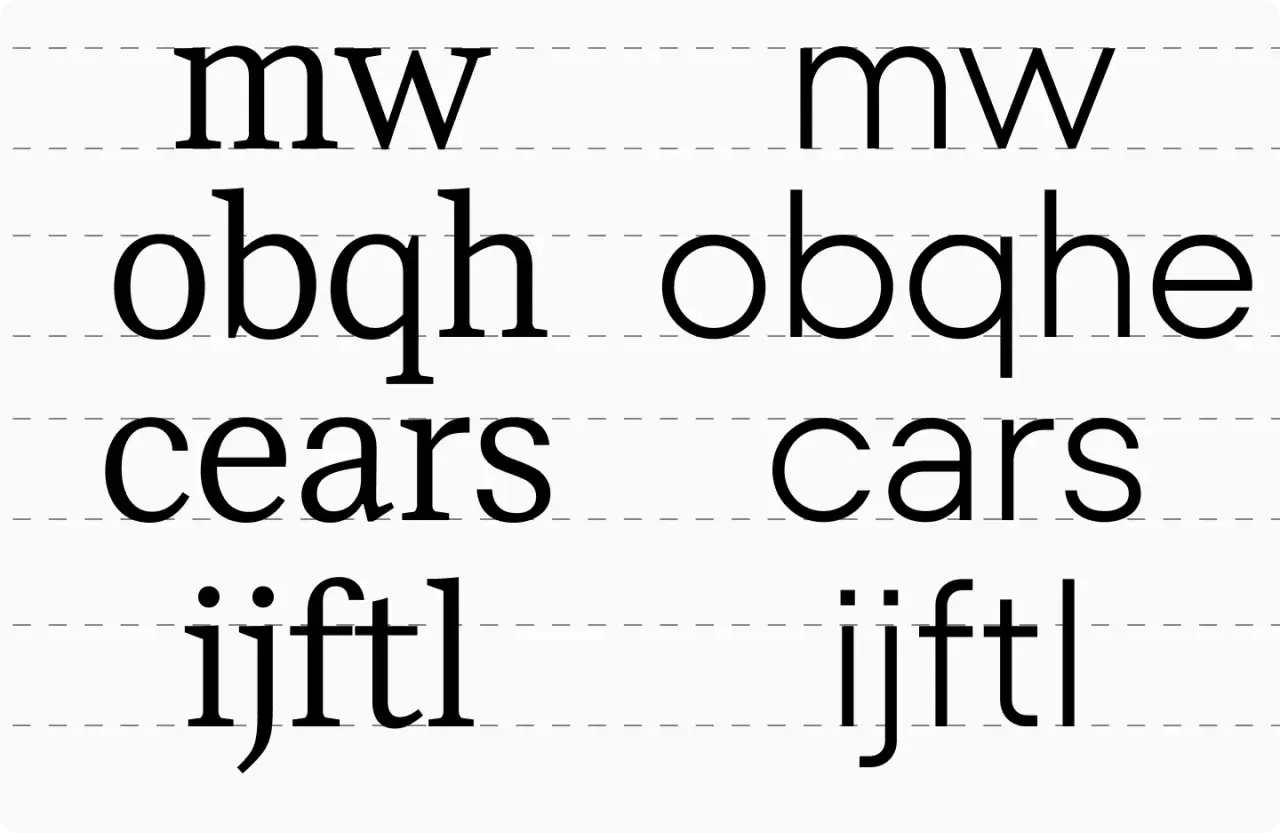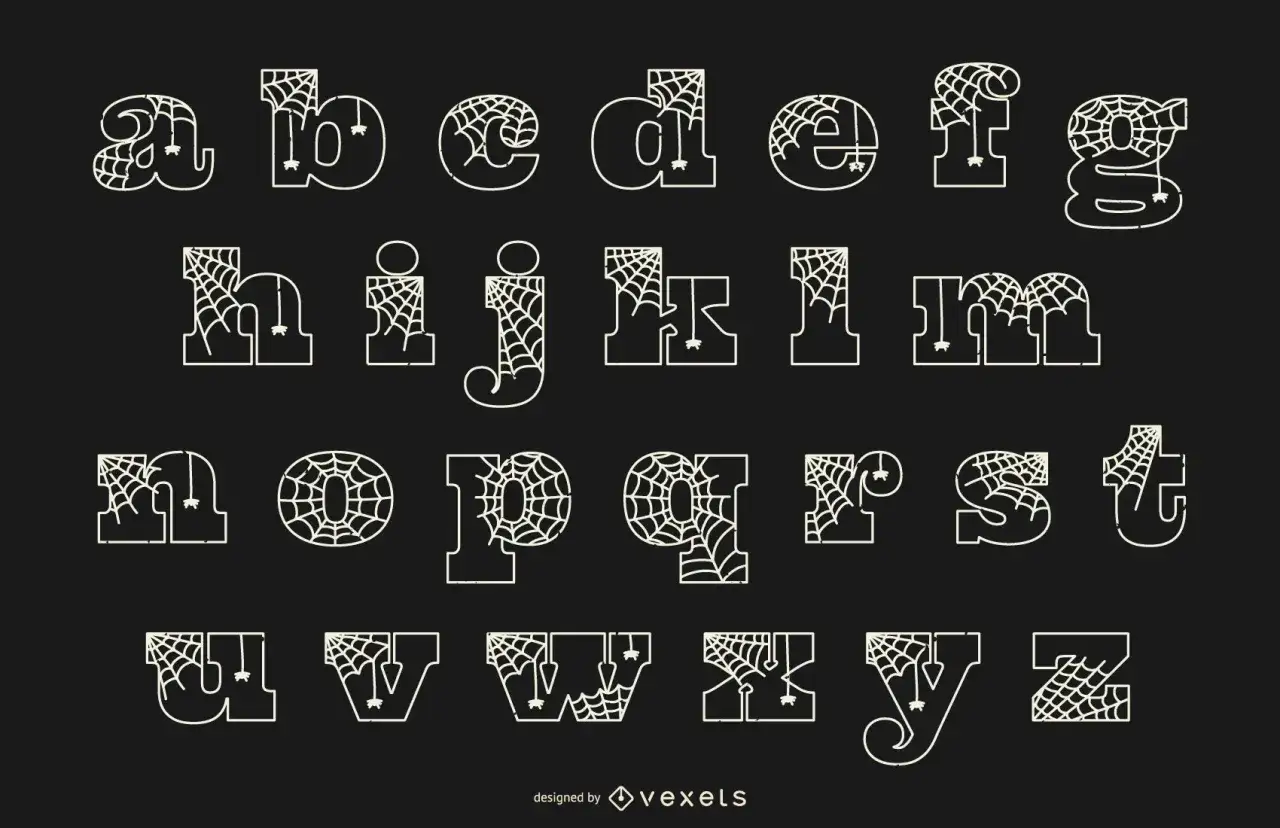
Minúsculas en tipografía - claves para leer y diseñar mejor
Líneas de texto con letras minúsculas: "mw", "obqh", "cears", "ijftl" y sus variaciones.
Las letras minusculas son la base silenciosa de casi todo lo que leemos: textos largos, etiquetas, carteles, notas y piezas de lettering. Cuando están bien resueltas, no llaman la atención; cuando fallan, el diseño entero se vuelve torpe o cansado. Aquí repaso qué son, cuándo conviene usarlas, cómo afectan a la tipografía y qué mirar antes de cerrar un proyecto visual.
Lo esencial de las minúsculas para leer y diseñar mejor
• La minúscula es la forma base del texto continuo y suele facilitar una lectura más fluida que la mayúscula sostenida.
• La mayúscula no sustituye a la minúscula: cumple funciones concretas y está mejor reservada para casos normativos o de énfasis real.
• En tipografía importan mucho la altura de x, el interletrado, el contraste y la apertura de las contraformas.
• En diseño y manualidades, una buena minúscula aporta cercanía, orden y limpieza visual sin perder personalidad.
• Los errores más frecuentes no están en la letra en sí, sino en el espaciado, la elección de fuente y la falta de intención.
Qué son las minúsculas y por qué siguen siendo la base del alfabeto
Yo las trato como la letra por defecto del texto corrido. La RAE considera la minúscula la forma base de la escritura y deja la mayúscula para los casos que marca la norma, no para decorar ni para compensar una composición floja. Esa diferencia parece pequeña, pero cambia por completo la manera en que se lee una página.
La minúscula no es solo una versión “más pequeña” de otra letra. Tiene rasgos propios: ascendentes, descendentes, aperturas internas y una silueta visual que el ojo reconoce con rapidez. Gracias a eso, una frase en minúsculas se sigue mejor que un bloque entero de mayúsculas, especialmente cuando el texto es largo o la pieza necesita parecer natural.
En la práctica, esto explica por qué casi toda la escritura cotidiana se apoya en minúsculas. Son más flexibles, más legibles y más cercanas al ritmo real del lenguaje. Con esa base clara, ya se entiende mejor cuándo conviene dejar que manden y cuándo hace falta combinarlas con otras formas.
Cuándo conviene escribir en minúsculas y cuándo no
La clave no es usarlas “siempre”, sino elegir la mezcla correcta según el objetivo. En un aviso breve, una mayúscula puede aportar presencia; en un párrafo, la minúscula casi siempre facilita la lectura. Yo suelo pensar primero en la función y después en el estilo.
Situación Qué suele funcionar Por qué
Texto corrido Minúsculas La lectura fluye mejor y el ojo reconoce antes la forma de cada palabra.
Títulos breves Minúsculas o combinación con versalitas La pieza se ve más cercana sin perder jerarquía.
Siglas y avisos Mayúsculas Dan más presencia visual y ayudan a destacar bloques cortos.
Marcas artesanales Minúsculas bien dibujadas Transmiten calidez, sencillez y un tono menos rígido.
Documentos formales Mayúsculas solo donde manda la norma Evita ruido visual y mantiene la corrección ortográfica.
La versalita merece una mención aparte: tiene la forma de la mayúscula, pero una altura cercana a la minúscula, así que funciona como un recurso híbrido muy útil en títulos, referencias o detalles tipográficos. No sustituye a todo lo demás, pero bien usada aporta equilibrio sin romper el tono general. Cuando esa decisión está clara, el siguiente paso es entender cómo se comportan las minúsculas dentro de la propia tipografía.
Cómo influyen en la tipografía y la legibilidad
En tipografía, la minúscula no solo ocupa espacio: construye ritmo. En Adobe, la referencia de x-height se usa precisamente para medir la altura de las minúsculas sin contar ascendentes ni descendentes, y ese dato explica por qué dos fuentes del mismo cuerpo pueden verse tan distintas. Una x-height alta suele hacer que el texto parezca más robusto y legible a tamaños pequeños; una más baja puede dar elegancia, pero exige más aire y más cuidado.
Yo suelo fijarme en cuatro cosas antes que en el “gusto” puro de la fuente: apertura de contraformas, contraste de trazos, interletrado y equilibrio entre ascendentes y descendentes. Las contraformas son los huecos internos de letras como a, e, o o p; si se cierran demasiado, la lectura se empantana. El interletrado es la distancia entre caracteres: si queda muy apretado, las palabras se vuelven un bloque; si queda demasiado abierto, la línea pierde cohesión.
Elemento Qué cambia Qué conviene buscar
Altura de x La proporción visual del cuerpo de las minúsculas Un equilibrio que mantenga claridad a tamaños pequeños
Contraformas Los espacios internos de letras como a, e, o, p Aperturas limpias que no se cierren con el peso de la fuente
Interletrado La distancia entre caracteres Suficiente aire para que la palabra respire
Contraste La diferencia entre trazos finos y gruesos Moderación en textos largos para no cansar la vista